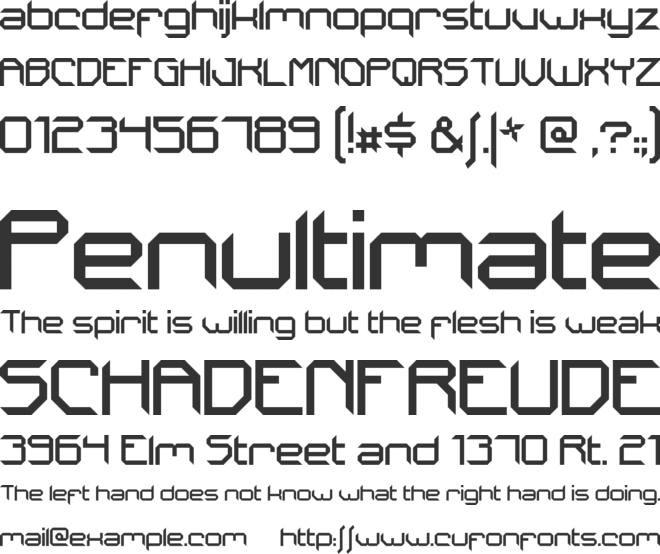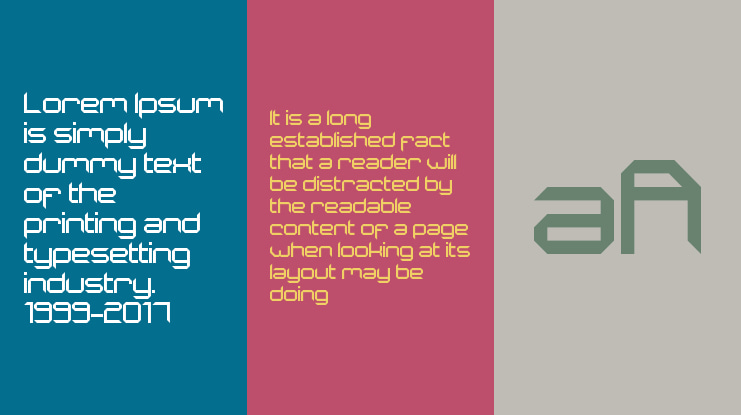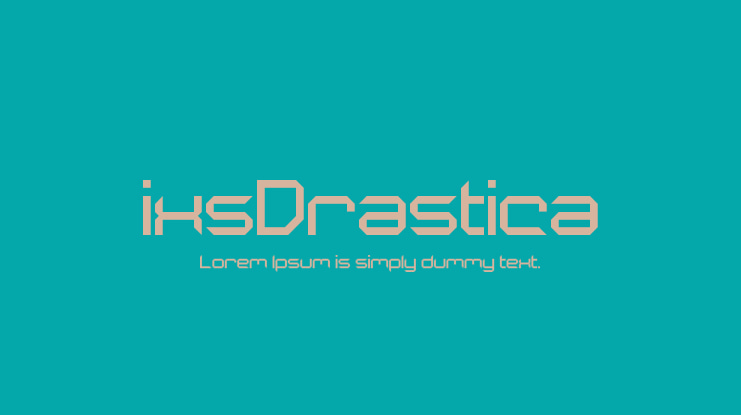
ixsDrastica Font
Diseño experimental de familia tipográfica desarrollada para por el grupo IXS. Libre para cualquier tipo de uso, salvo proyectos estrictamente comerciales.